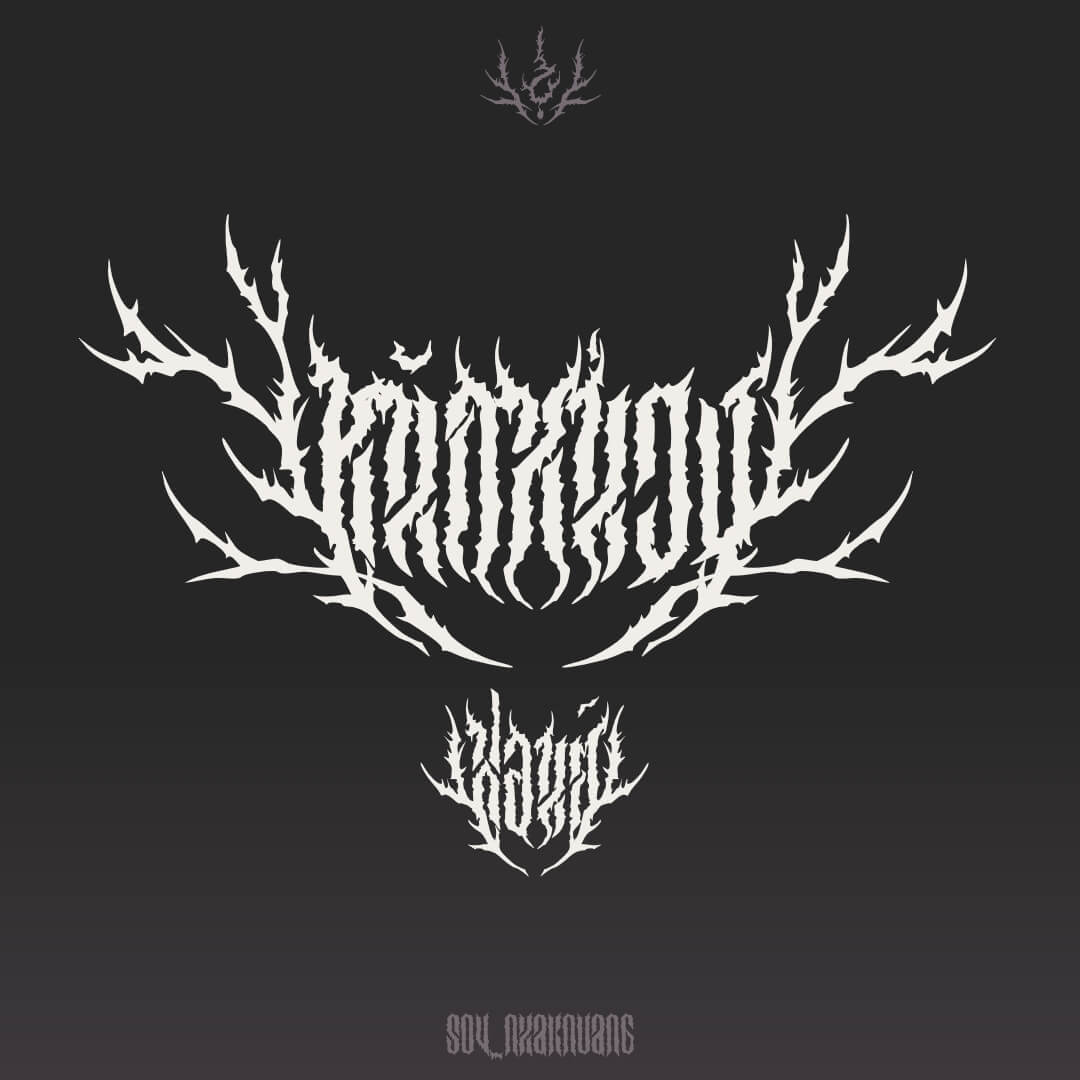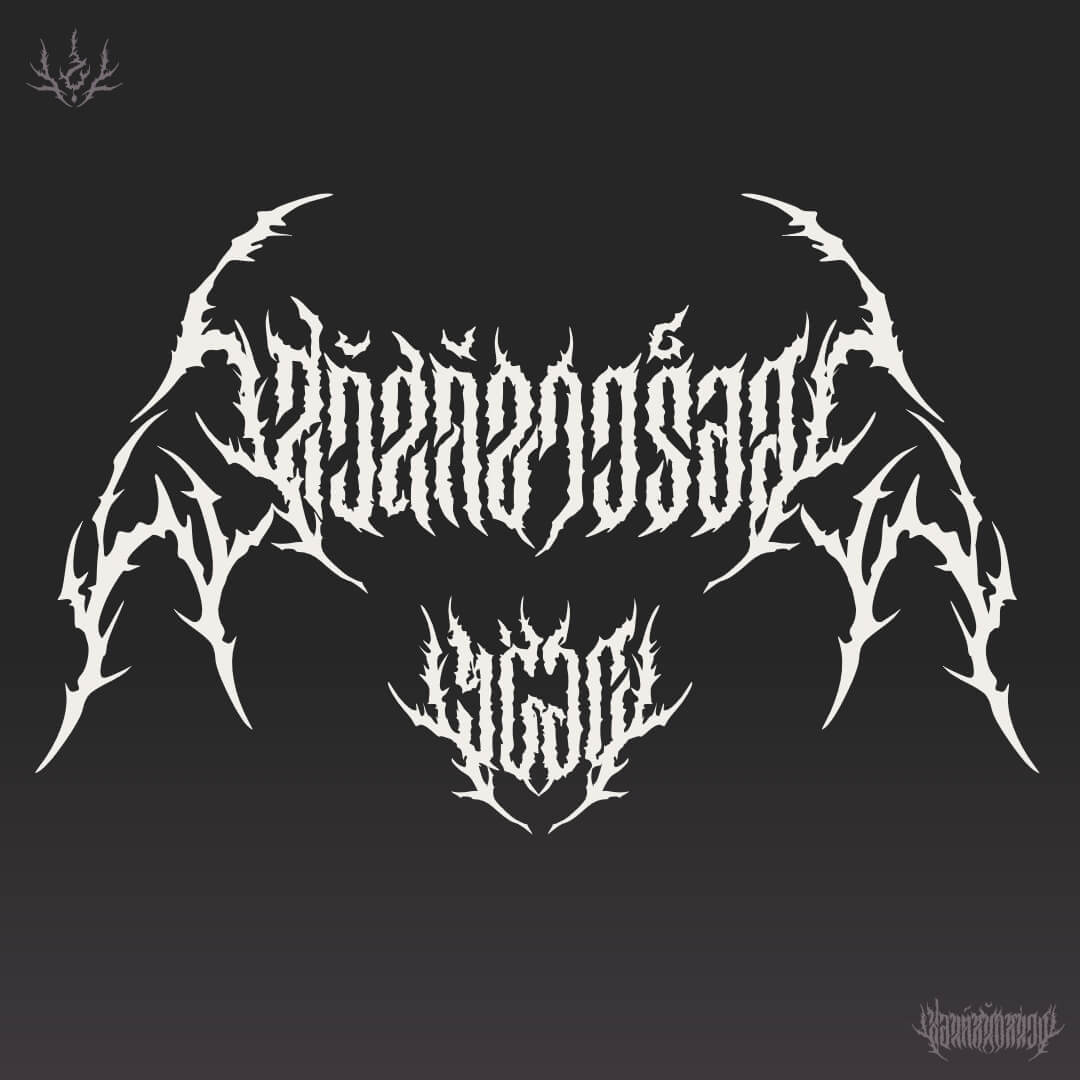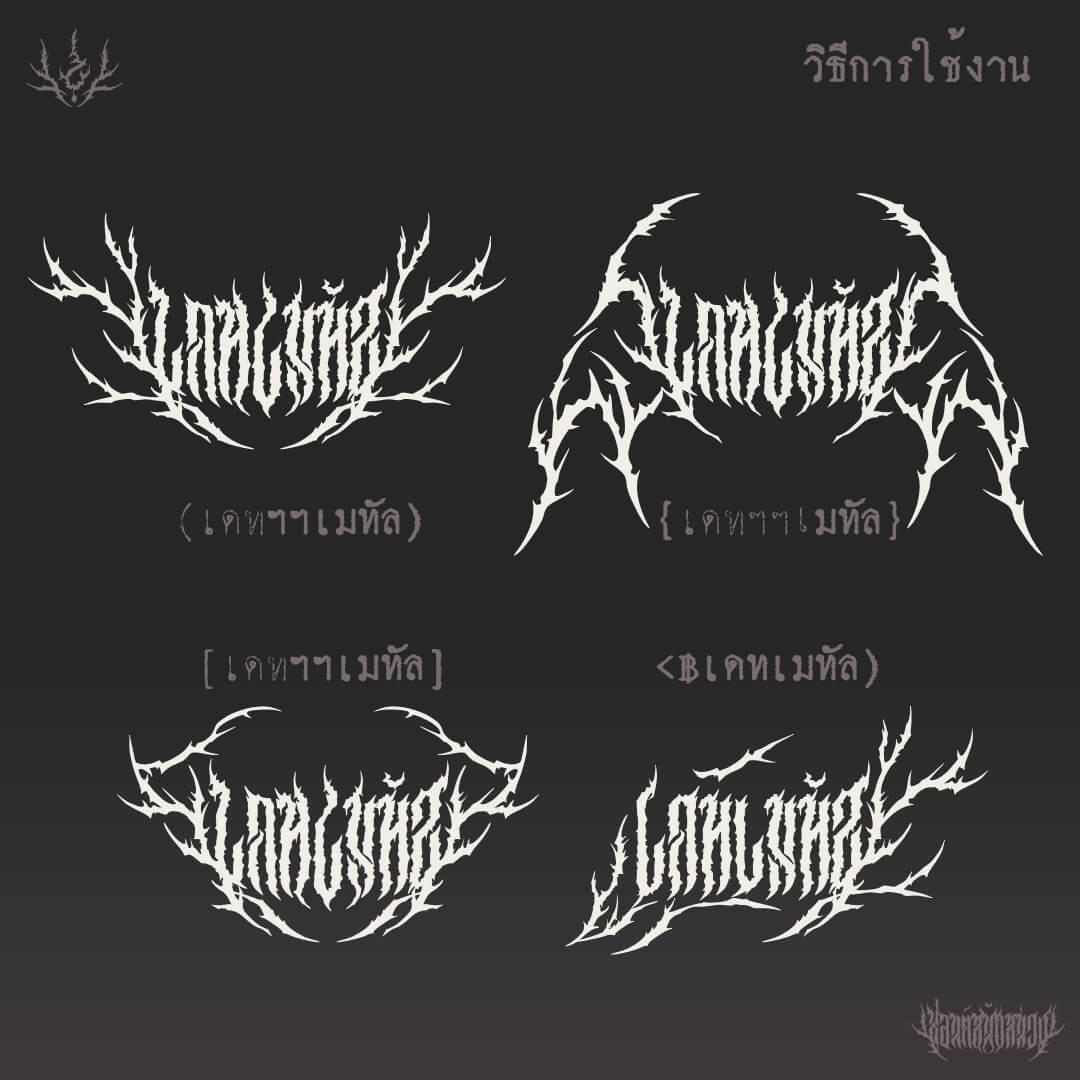
หนักหน่วง (SOV_NhakNuang)
หนักหน่วง – ฟอนต์แนว logo วง Heavy Metal ครึ่งซ้ายใช้ตัวปรกติ ครึ่งขวาใช้ตัว bold ถ้ามีอักษรตรงกลาง ให้กด ฯฯ นำหน้า เติมวงเล็บแบบต่างๆ ได้